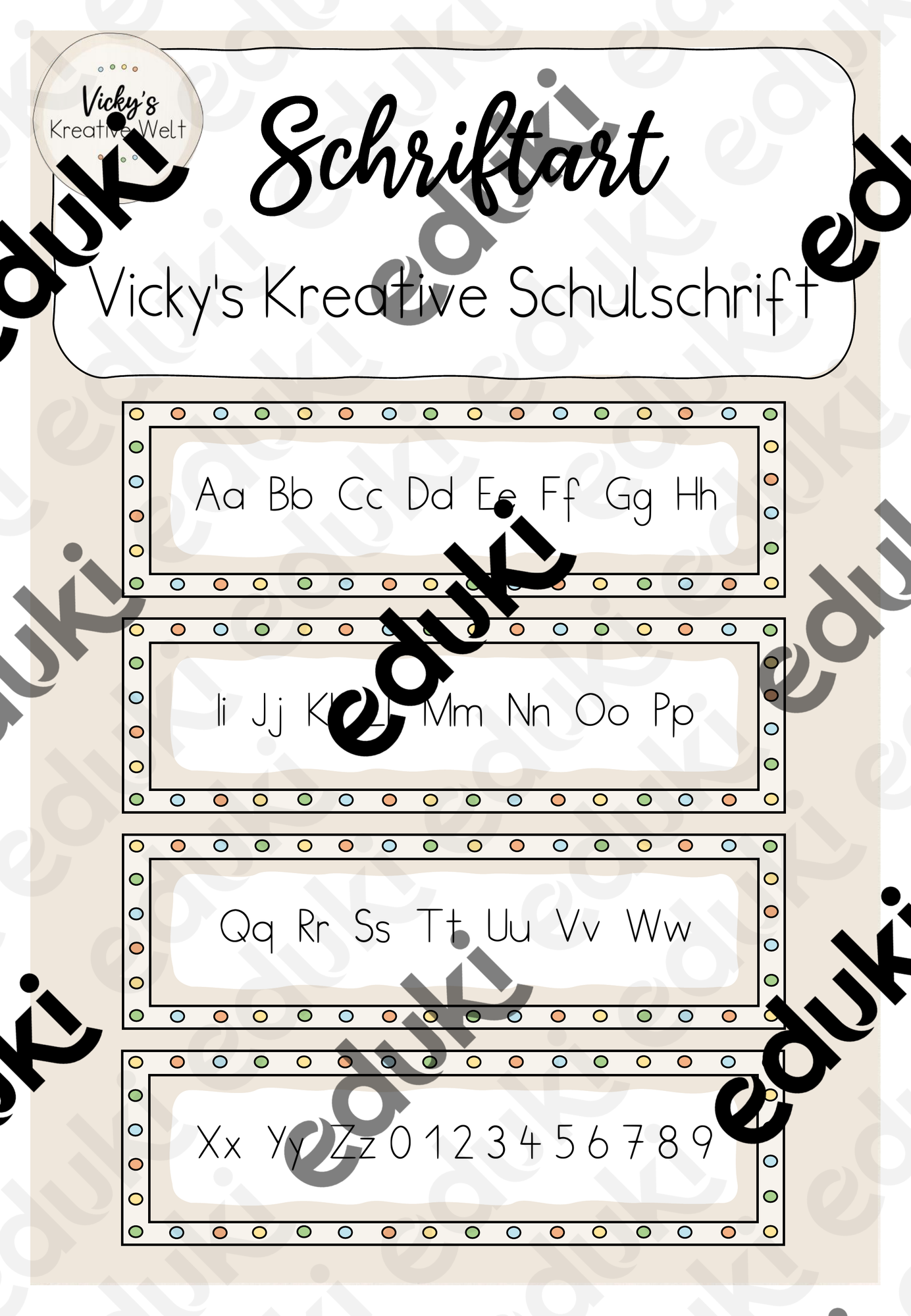
selbst erstellte Schriftarten - Schriftart - Vicky's Kreative Schulschrift - ✨ Vicky's Kreative Welt ✨ - Deckblatt
Dieses Material enthält die Schriftart "Vicky's Kreative Schulschrift" und ist für Grundschulkinder gut und leicht lesbar.
Schriftart - Vicky's Kreative Schulschrift